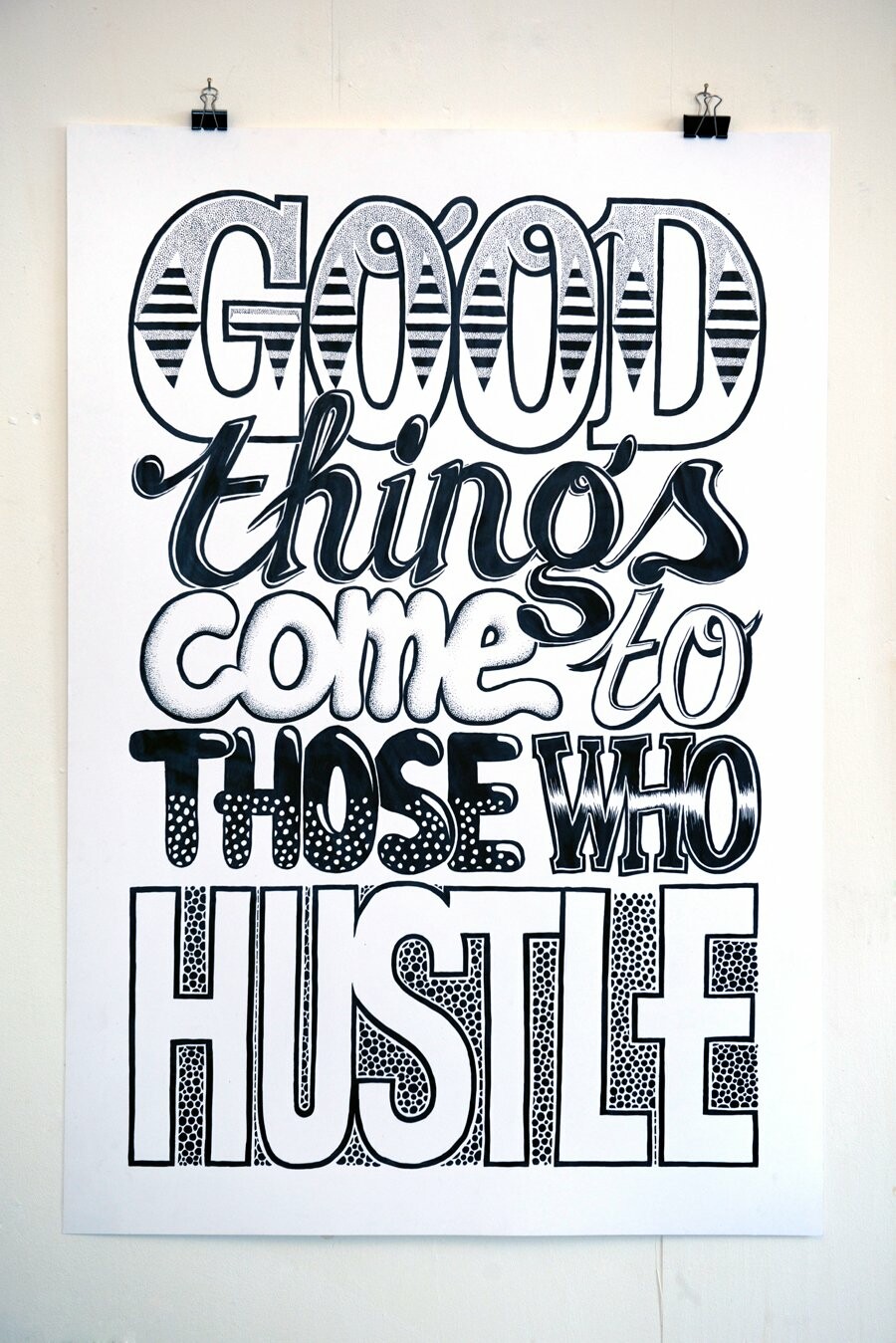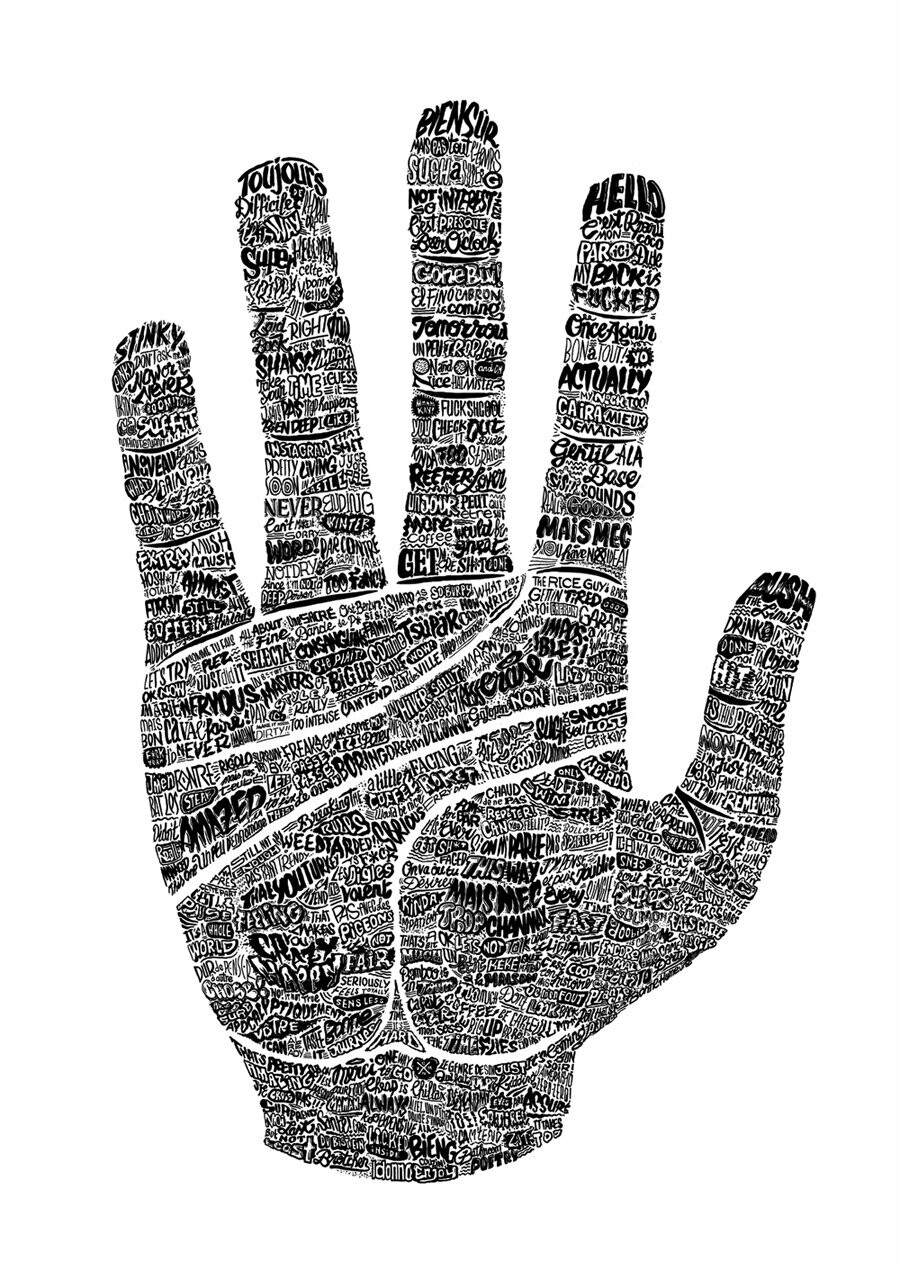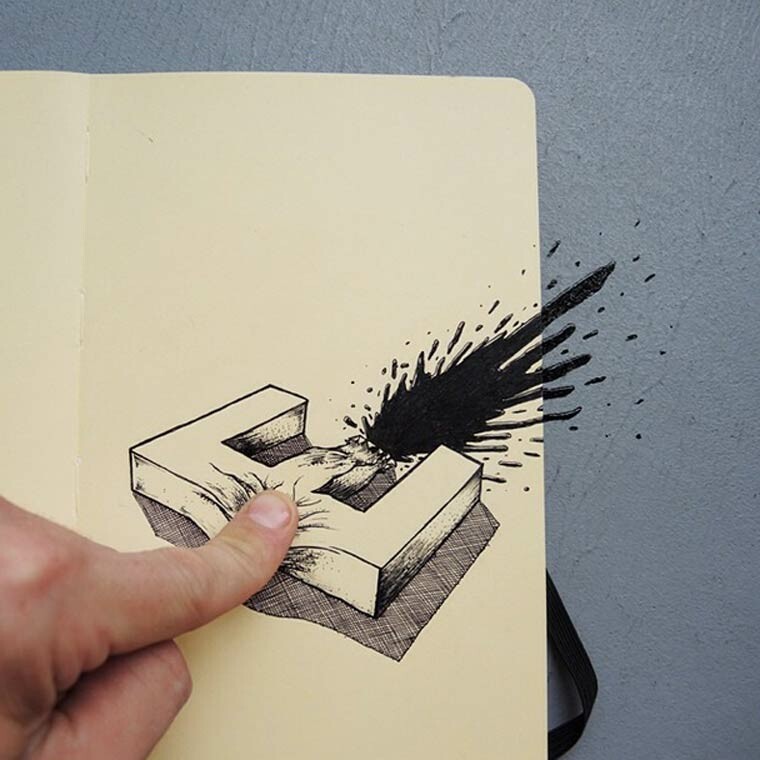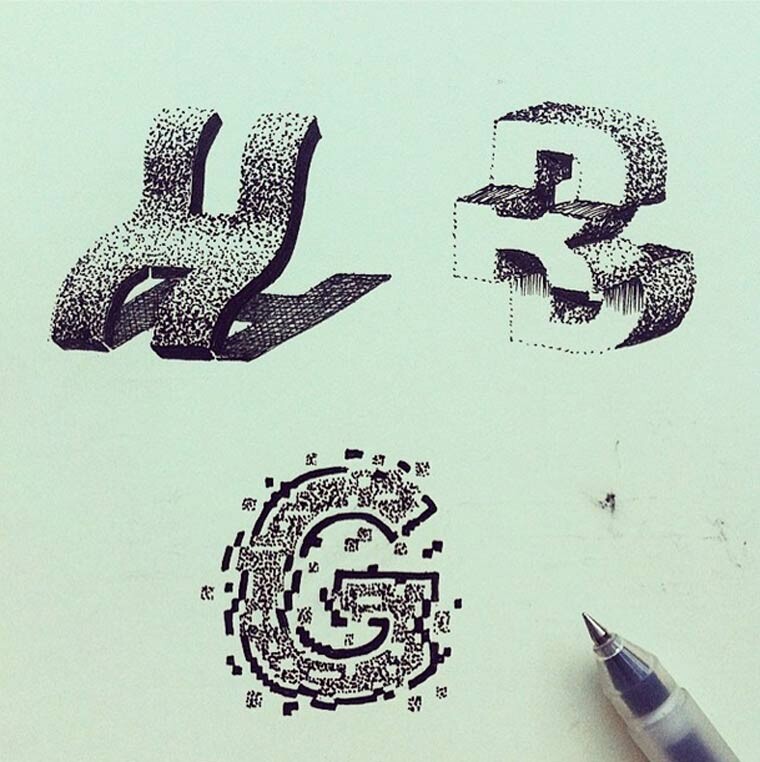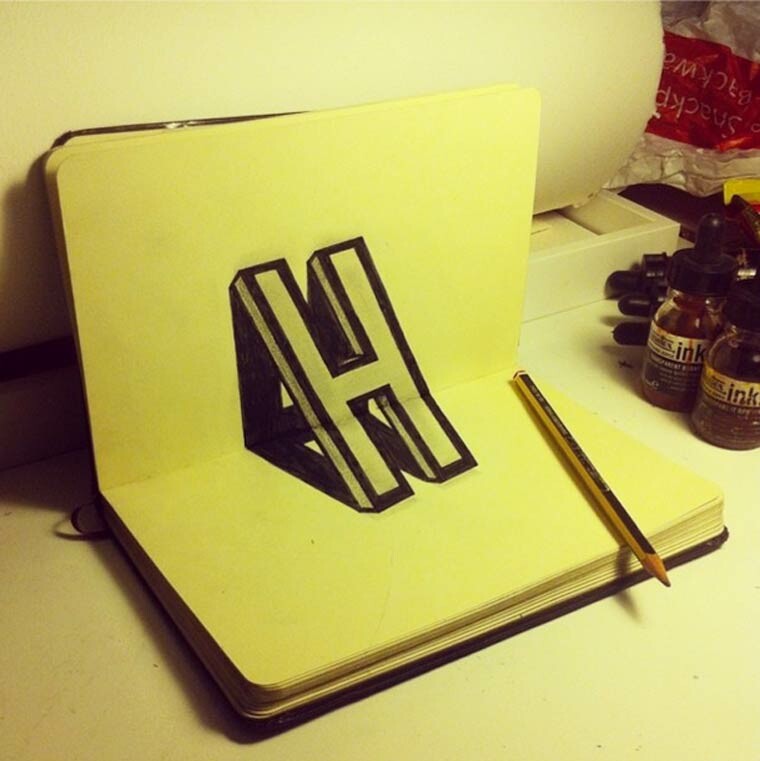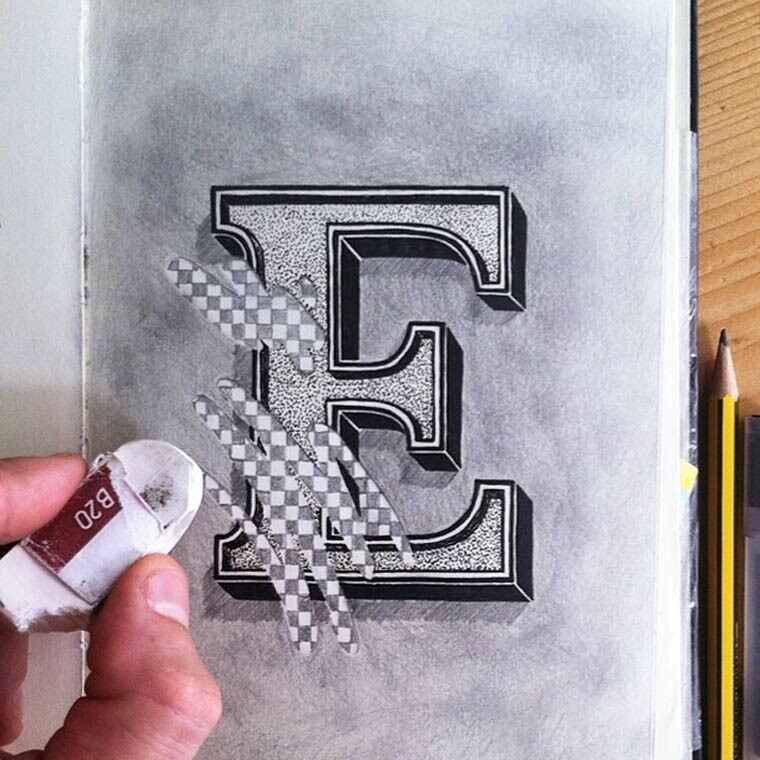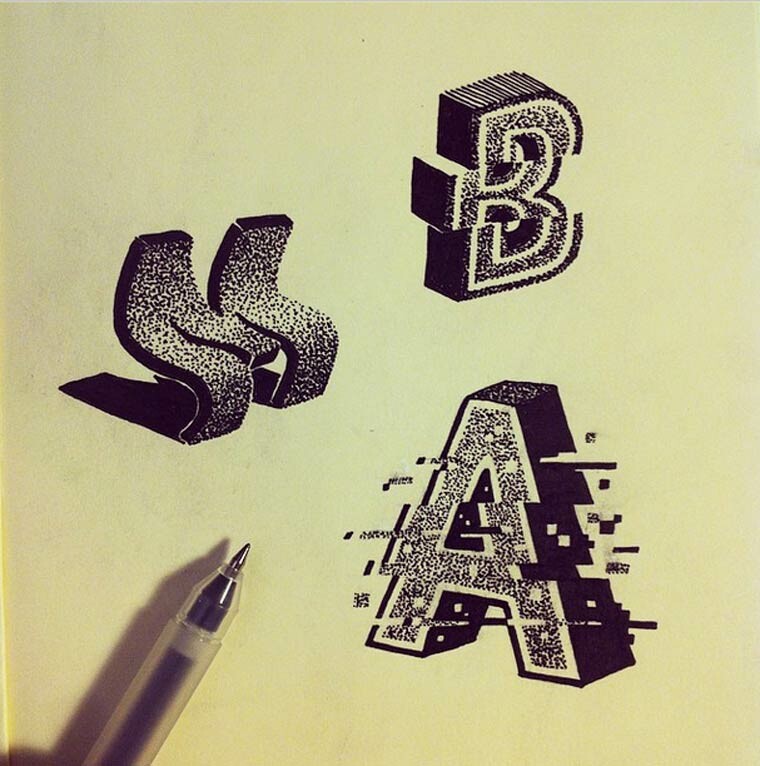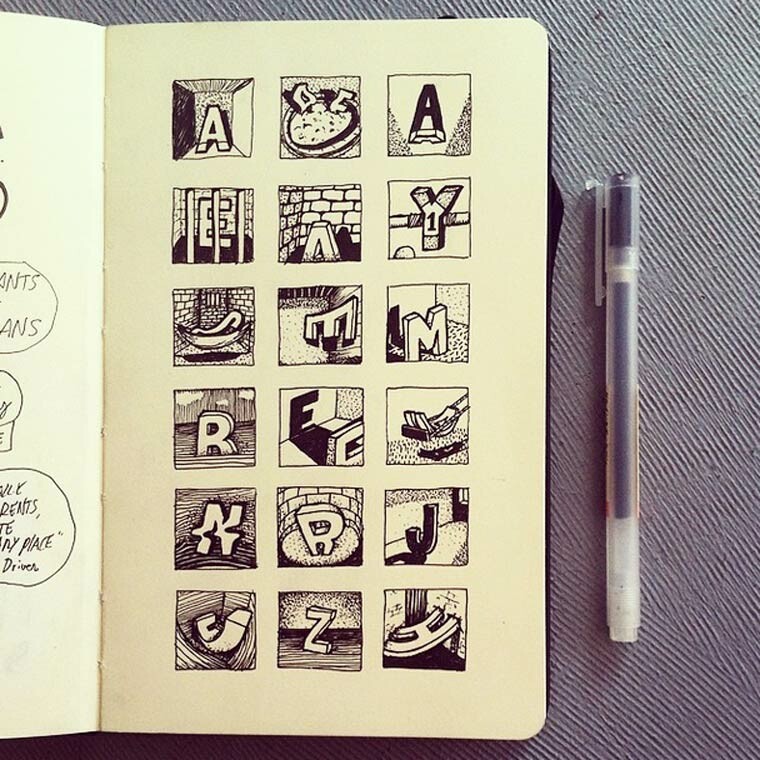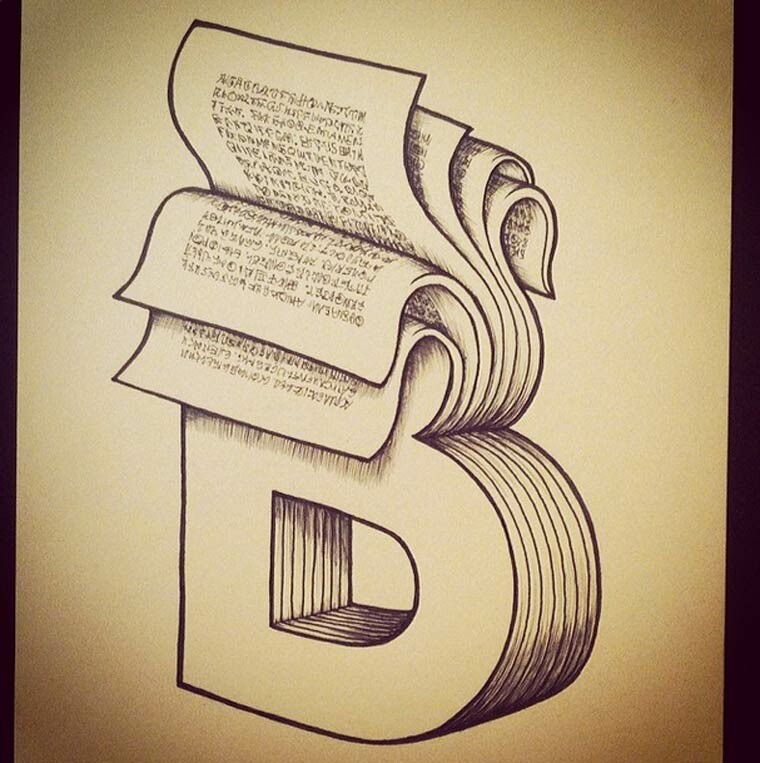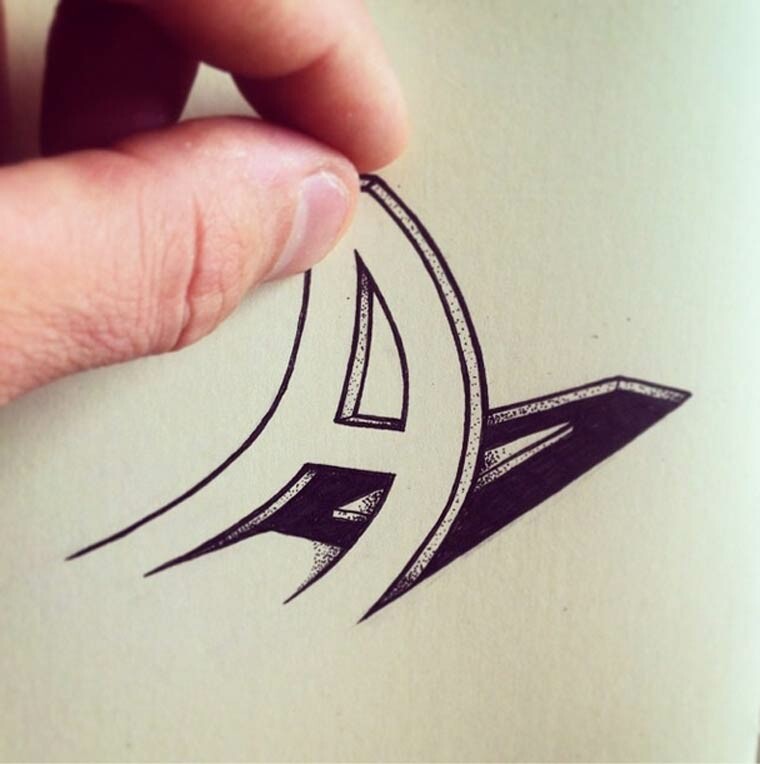
Σπάζοντας πλάκα με την τυπογραφία
O ταλαντούχος καλλιτέχνης, street artist, και graphic designer Cyril Oz, aka Rylsee (ψάξτε τον λίγο παραπάνω, αξίζει τον κόπο) αρέσκεται, ανάμεσα σε άλλα, να πειραματίζεται συνεχώς με την έννοια της γραμματοσειράς και της τυπογραφίας.
Αυτή τη φορά φαίνεται να περνάει τον χρόνο του σπάζοντας πλάκα, διαστρεβλώνοντας, ανατινάζοντας και... απάγοντας τα γράμματα του αλφαβήτου single- handedly.